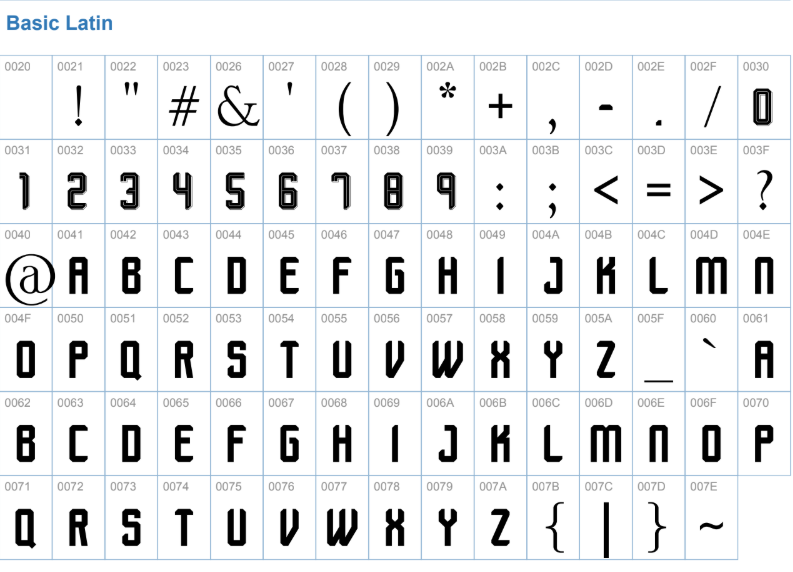
A nova coleção 2026 chegou com tudo, e a identidade visual do Adidas Away não brinca em serviço. A tipografia oficial da temporada traduz em cada caractere a agressividade e a fluidez que a torcida vai ver nos estádios e nas telas. É aquela fonte que mistura tradição e futuro, nascida para gritar gol sem abrir a boca.
Estilo visual da tipografia
A Adidas Away 2026 abusa de traços geométricos com cantos levemente arredondados, criando um contraste equilibrado entre modernidade e legibilidade. Os números têm estrutura condensada, com hastes verticais largas que garantem leitura imediata mesmo nas transmissões em movimento ou em ângulos fechados.
O desenho das letras e números lembra blocos aerodinâmicos, com recortes estratégicos que dão ritmo ao conjunto. É uma fonte que transpira velocidade controlada — estilo “corredor explosivo” — perfeita para o padrão atual de transmissão em 4K e mobile.
Aplicação no uniforme
Home (titular): Numeração branca com contorno escuro, aplicada em alto relevo na parte central do dorso. O efeito emborrachado mantém a legibilidade sob luz intensa.
Away (reserva): Versão chapada em preto fosco sobre fundo claro, sem contorno adicional, garantindo contraste máximo em estádios abertos.
Third (terceiro uniforme): A fonte ganha acabamento metálico em dourado ou cobre, dependendo da iluminação, com microtextura que brilha nos close-ups da transmissão.